适合AR/VR的字体
在增强现实(AR)与虚拟现实(VR)中使用文本面临着新的设计挑战,这些挑战几乎与其他任何现有的媒介截然不同。Monotype的字体创意总监Steve Matteson筛选了可辨识度高,风格多样的字体,为AR / VR游戏、应用程序或者用户界面提供了可信赖的选择。
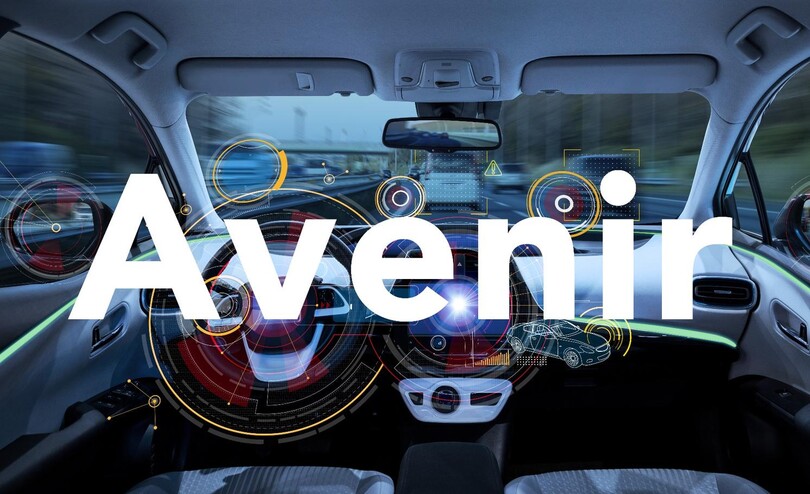
Avenir™
在法语中,Avenir是“未来”的意思,它暗含着该字体的部分含义来自Futura。但与Futura不同,Avenir不是纯粹的几何字体,它的垂直笔划要比水平笔划更厚重,“o”不是一个正圆,而且升部被缩短了。Avenir是最清晰易读的几何非衬线体的代表。Avenir弱化了纯几何体所带来的挑战,着重强调清晰的字形、开放的形式以及加宽的字间距。Avenir很适用于AR / VR中的扩展文本,也能为家用电器或物联网的界面增添点现代气息。
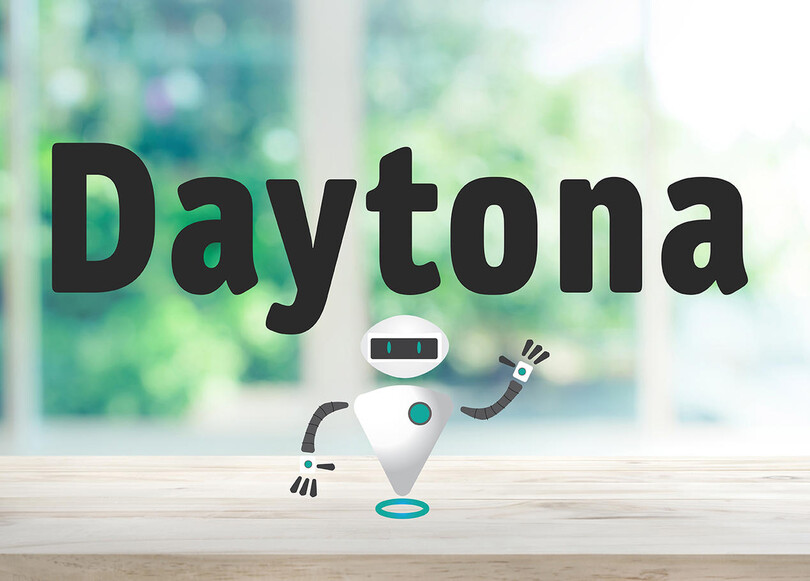
Daytona™
Daytona字体系列源自于Jim Wasco的一个愿望,他希望为视频和屏幕使用设计一种易读的字体。由于出色的易读性,也使它成为了数字用户界面和各种打印应用的理想之选。Daytona圆润的形式给人一种非正式的感觉,使原本现代的设计风格看起来更加柔和。这使它成为适用于儿童AR / VR游戏或应用程序的完美字体。这种字体最初是为导航和导视系统而设计的,也适用于抬头显示器。即使在一个令人紧张的未来虚拟现实体验中,Daytona也可以为用户提供更友好的展示。
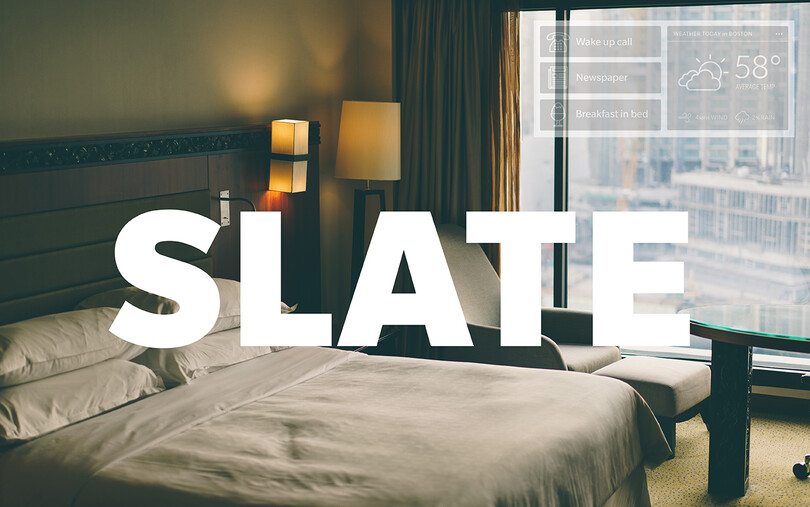
Slate™
Slate字体家族将出色的功能及视觉的优雅融合成一种卓越的交流工具。Slate是Rod McDonald的作品,Rod McDonald是一位屡获殊荣的字体设计师和刻字艺术家。在McDonald四十年的职业生涯中,他曾经参与过加拿大国家盲人研究(CNIB)所开展的字体易读性和可读性研究项目,通过这个项目,他学习到能够最大限度地提高字符易读性及文本可读性的设计特征。即使在AR/VR等具有挑战性的技术环境中,Slate也能为用户提供舒适的阅读体验。Slate的现代风格在应用程序界面、体验式演练或者AR应用程序过滤器中都能很好地发挥作用。
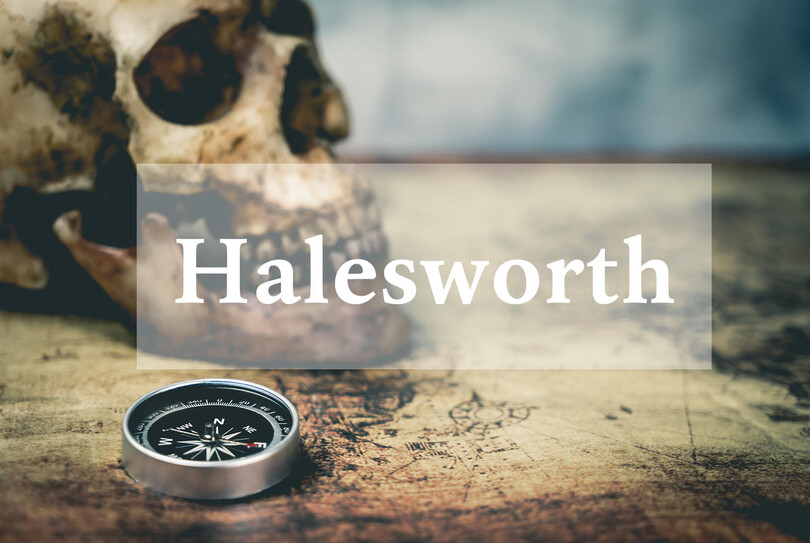
Halesworth™
要设计一种能唤起历史或学术共鸣的虚拟体验吗?Halesworth是由Carl Crossgrove设计的一款威尼斯旧式书籍字体,专为在屏幕上舒适阅读而设计。Halesworth保留了威尼斯风格优美、大方的比例,并优化了细节以获得最佳表现,这些使其成为了在VR环境中长篇文本的绝佳选择。这款字体减少了由极细的笔划(strokes)、开放的字怀(counters)、完美的流线以及坚实的衬线形成的对比。Halesworth风格优雅古典,但从屏幕的任何视角都可以舒适地阅读,是AR/VR的理想之选。
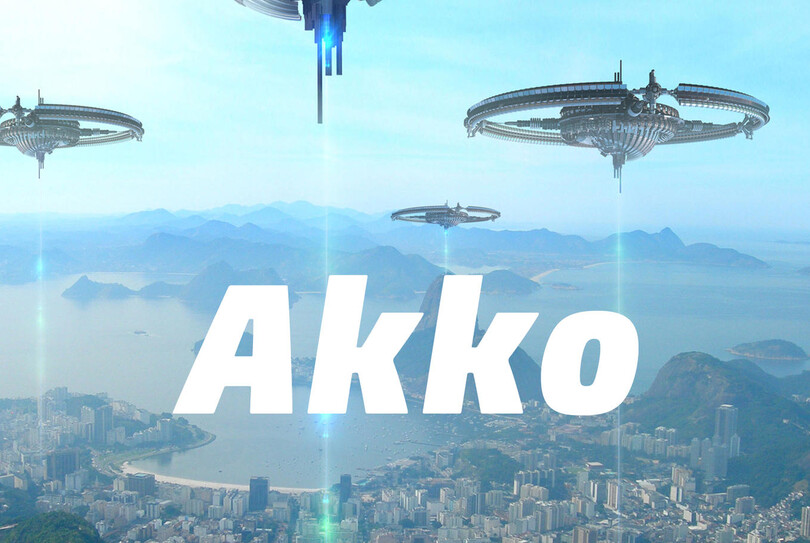
Akko™
需要为未来设计UI吗?没有比Akko字体更适合的了。Akko现代与开放式的设计有助于在VR情境中出现的各种视角下进行阅读。Akko的设计采用了非常开放的字怀以及很高的x字高,这符合市场对具有“技术”外观的新型无衬线体的需求。由此设计出来的字母简单紧凑,可以在布局上节省版面空间。Akko科技前沿的外观与其节省空间的特性相结合,又使其成为未来AR / VR游戏或体验的可靠之选。
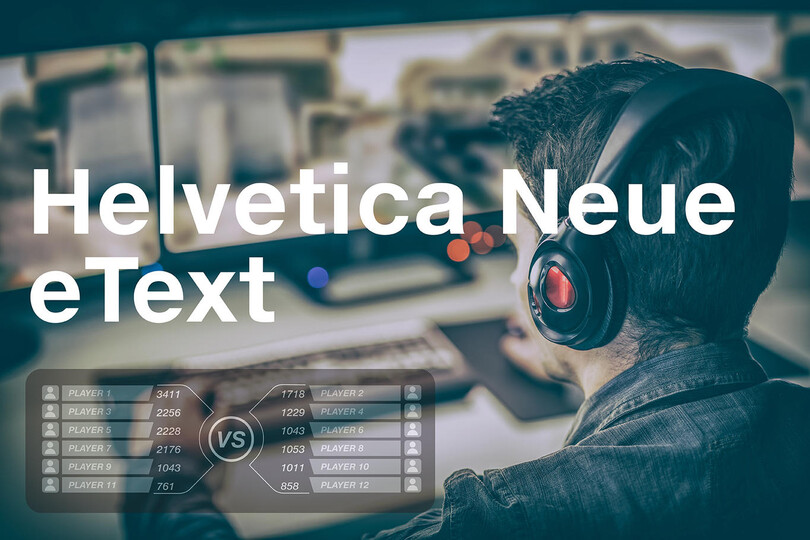
Helvetica eText™
Helvetica™无处不在,它是瑞士怪诞风格字体的旗舰产品。通过先进的字体微调(hinting)技术、扩展字符、修改线条粗细和x-字高,“e-text”减少了通常在风格上存在的易读性障碍,从而优化智能手机、平板电脑或电子阅读器的易读性。Helvetica eText在表现风格时有助于阅读,它尤其适用于网格排版,如在游戏中显示分数或健康指数,或者虚拟电子商务体验。